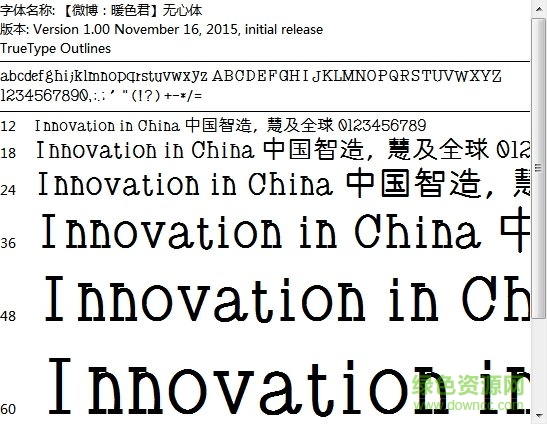
無心體是一款類似古書詩經(jīng)文字的娟秀中文字體,字體頗有隸書和篆書字體結(jié)合的優(yōu)美造型,給人一種十分質(zhì)樸復古的精彩視覺呈現(xiàn),快來綠色資源網(wǎng)試試吧!
無心體是微博【暖色君】推出的一款藝術(shù)字體,兼具手寫字體和網(wǎng)頁字體的特色,給人十分清爽大方的外觀,字庫完整,支持中英文輸入,能滿足大家日常生活的多種需求!
無心體是一款隸書風格的字體,字體簡潔耐看,適合閱讀,出自于暖色君字體系列,可用于平面設(shè)計、海報設(shè)計,包裝設(shè)計等場合,也可以用于手機字體的設(shè)置,閱讀效果更佳。